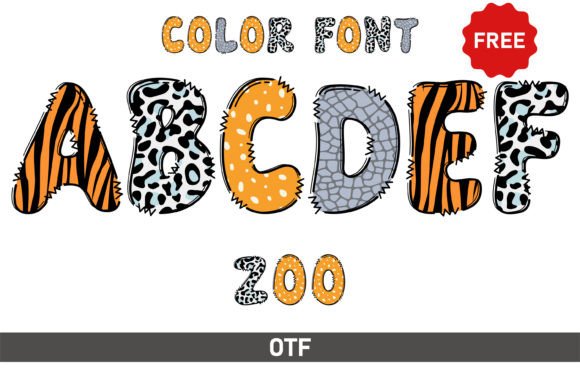
Zoo
Ulasan Lengkap Font “Zoo” – Pilihan Tepat untuk Desain Playful dan Artistik
Jika Anda sedang mencari font yang dapat menambah sentuhan ceria dan artistik pada proyek kreatif, Zoo menjadi pilihan yang sangat tepat. Font ini dirancang khusus untuk mengekspresikan keceriaan, sehingga sangat cocok untuk children’s books, poster, undangan, kartu ucapan, serta desain grafis lainnya yang memerlukan nuansa ringan dan mudah dibaca.
Keunggulan Utama Font Zoo
- Gaya Playful & Whimsical: Bentuk huruf yang melengkung dan berwarna membuat tulisan terasa hidup dan mengundang senyum.
- Keterbacaan Tinggi: Meskipun memiliki karakter yang unik, Zoo tetap mudah dibaca, cocok untuk audiens anak-anak.
- Versatilitas Warna: Tersedia versi black (monokrom) yang kompatibel dengan Cricut Design Space dan mesin pemotong lainnya, serta versi color yang mendukung Photoshop, Illustrator, Silhouette, dan Inkscape.
Ideal untuk Proyek Berikut
- Ilustrasi buku anak‑anak
- Poster acara keluarga atau festival
- Undangan pernikahan tema vintage‑playful
- Kartu ucapan ulang tahun dan hari raya
- Desain merchandise seperti t‑shirt dan tote bag
Kesimpulan
Font Zoo tidak hanya menambah estetika visual, tetapi juga meningkatkan engagement audiens melalui tampilan yang menyenangkan dan mudah dicerna. Baik Anda seorang desainer grafis profesional, guru, atau hobbyist, Zoo memberikan fleksibilitas dan kualitas tinggi yang dapat diandalkan dalam setiap proyek kreatif.